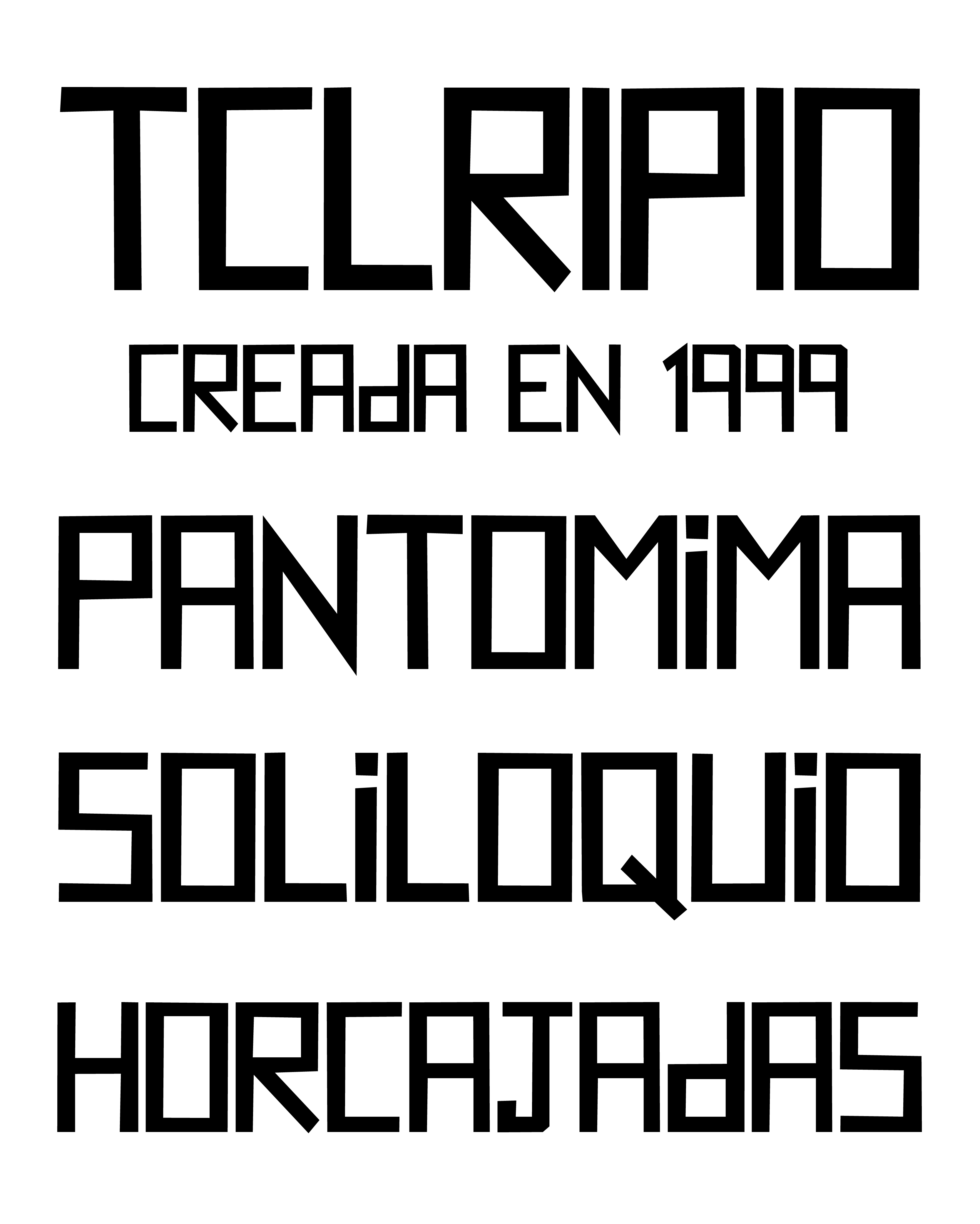
| Descripción | Tipografía creada como parte del proyecto “Tipografías Urbanas Populares Chilenas”, cuyo objetivo es rescatar las letras pintadas a mano de las calles de Chile y que cubre todo tipo de carteles, etiquetas y anuncios. Este tipo de cartelería está muy extendida en todos los sectores de nivel económico medio y bajo, y se crea con fines informativos o para publicitar un producto o servicio específico. |